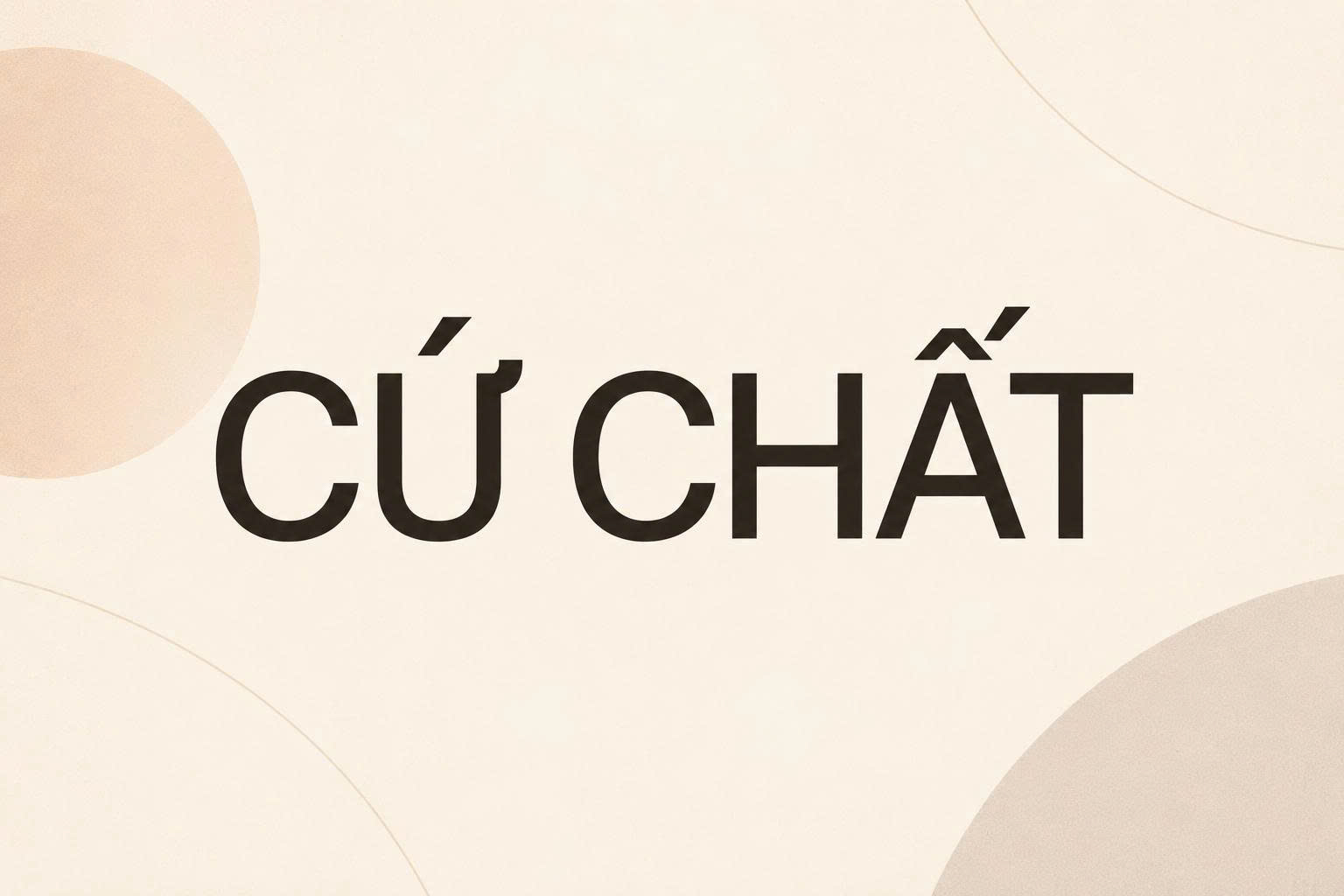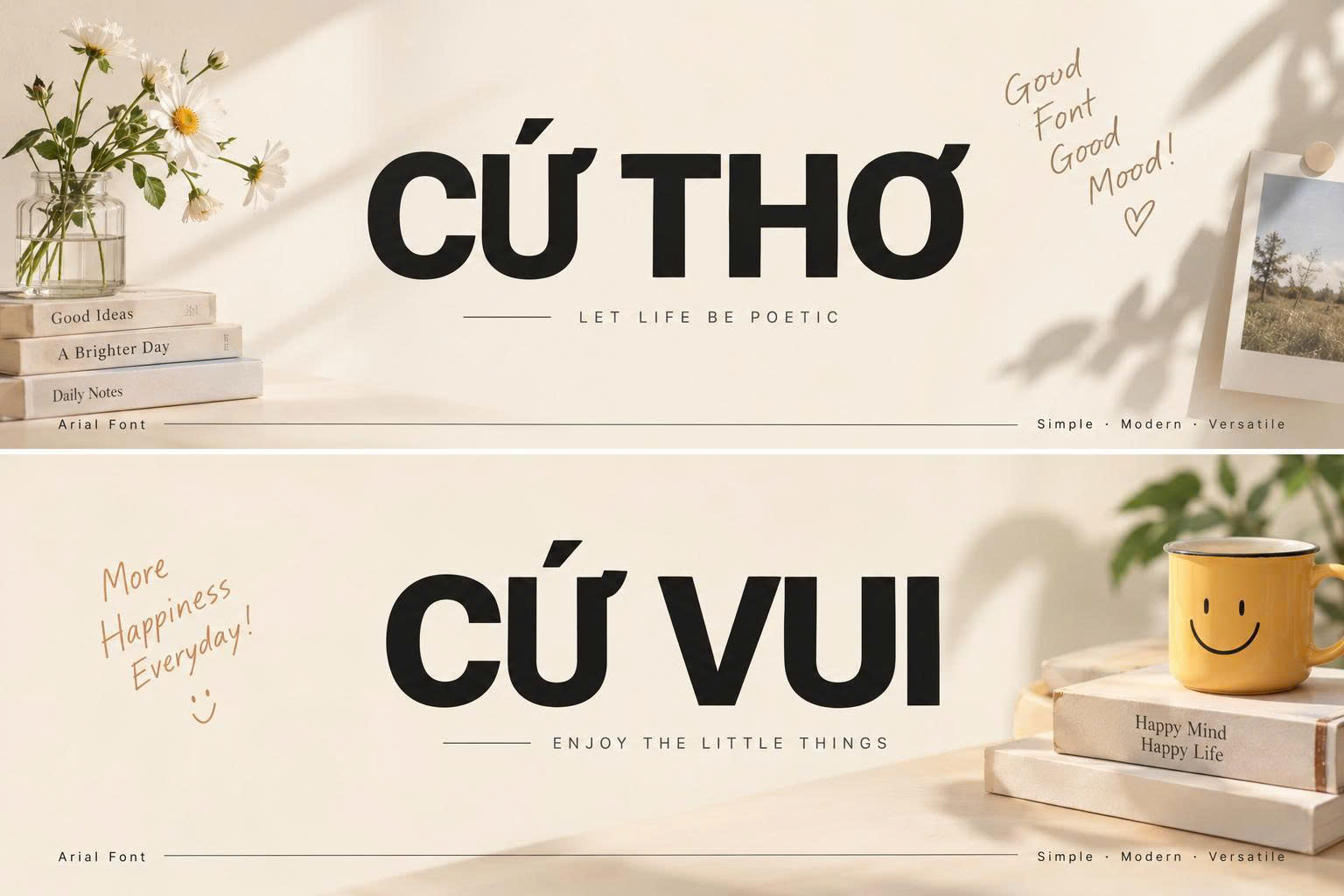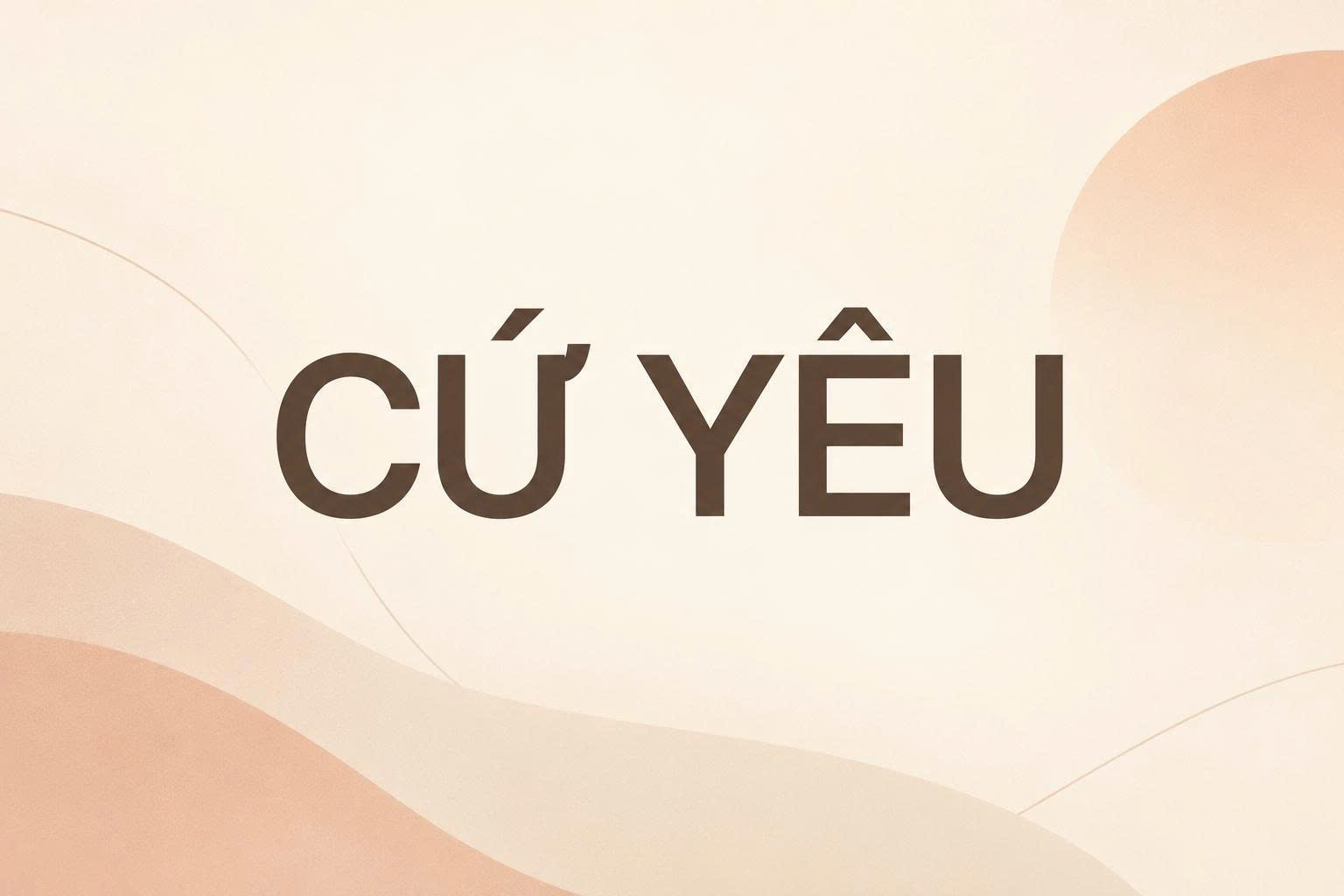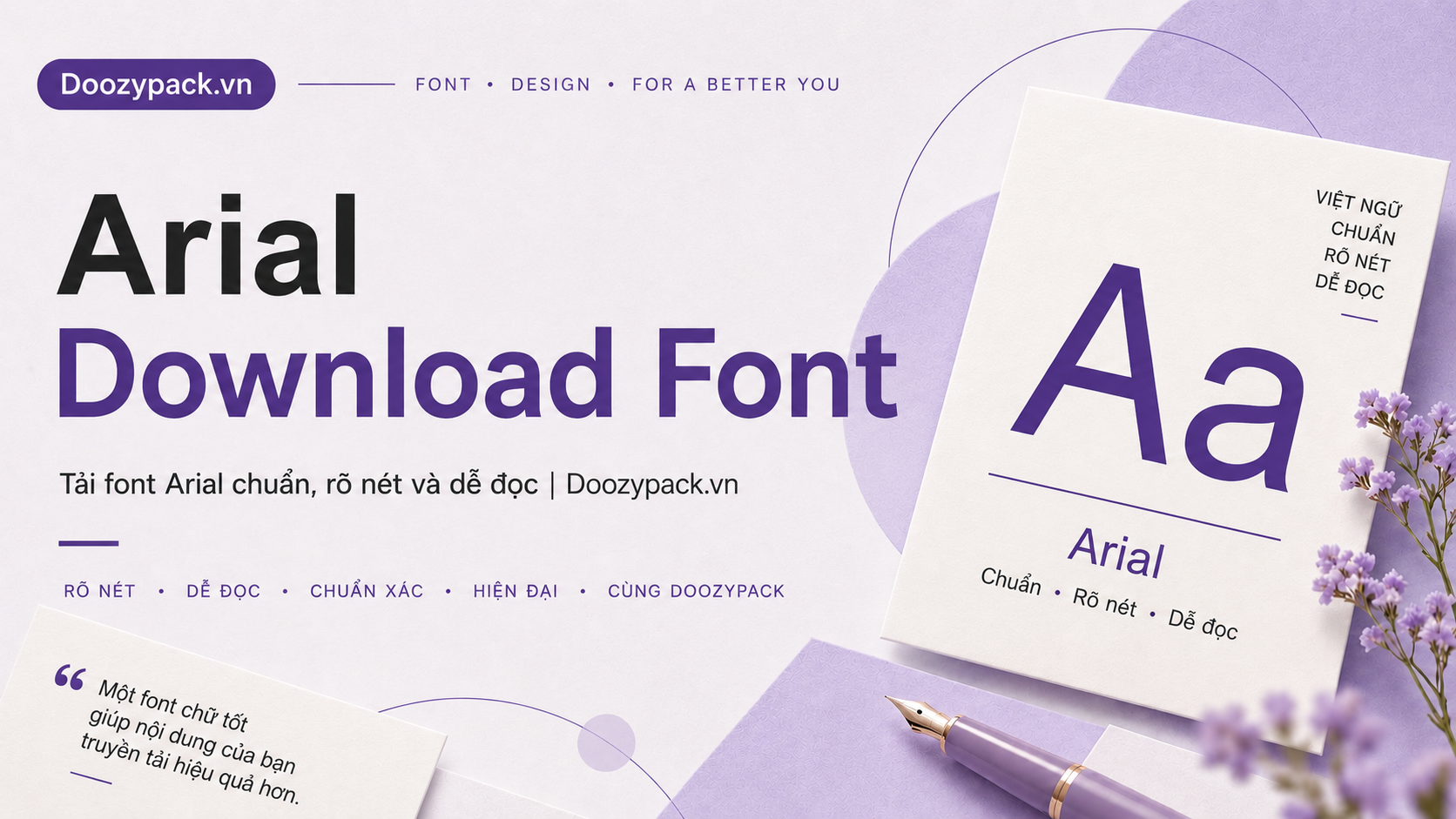
Arial download font là từ khóa được tìm kiếm nhiều nhất khi designer và nhân viên văn phòng cần một bộ phông chữ không chân (Sans-serif) tiêu chuẩn, hiện đại và có độ tương thích tuyệt đối. Được thiết kế bởi Monotype, Arial đã trở thành “phông chữ quốc dân” nhờ cấu trúc chữ minh bạch, rõ nét và cực kỳ dễ đọc trên mọi thiết bị. Doozypack.vn chia sẻ link download font Arial trọn bộ, bao gồm các biến thể quan trọng như Narrow, Bold và Unicode MS để bạn hoàn thiện các bản thiết kế bao bì và văn bản chuyên nghiệp nhất.
Đặc điểm thiết kế vượt trội của phông chữ Arial
Arial không chỉ là một phông chữ hệ thống đơn thuần; nó là kết quả của sự nghiên cứu về tỉ lệ hình học để mang lại trải nghiệm thị giác trung tính và chuyên nghiệp nhất.
Tính đa dụng và độ dễ đọc cực cao
Đặc trưng lớn nhất của Arial là các đường nét dứt khoát, độ dày nét đồng đều và không có các chi tiết rườm rà. Thiết kế này giúp mắt người nhận diện ký tự nhanh chóng, giảm thiểu tình trạng mỏi mắt khi đọc các khối văn bản dài. Tại Doozypack.vn, chúng tôi luôn khuyên khách hàng sử dụng Arial cho các phần nội dung quan trọng trên bao bì như hướng dẫn sử dụng, bảng thành phần dinh dưỡng hoặc địa chỉ sản xuất.
Sự tương thích tuyệt vời trên mọi hệ điều hành
Arial là phông chữ tiêu chuẩn trên cả Windows và macOS. Việc sử dụng Arial giúp bản thiết kế của bạn giữ nguyên định dạng khi chuyển đổi giữa các máy tính khác nhau. Điều này đặc biệt quan trọng trong quy trình in ấn tại xưởng, giúp hạn chế tối đa rủi ro lỗi nhảy chữ hoặc lỗi font khi mở file sản xuất.
Tổng hợp các biến thể Arial phổ biến nhất hiện nay
Hệ gia đình font Arial cung cấp nhiều biến thể đặc thù để giải quyết từng bài toán không gian khác nhau trong thiết kế:
- Arial Unicode MS: Đây là bản “full” nhất hỗ trợ hàng chục nghìn ký tự của nhiều ngôn ngữ khác nhau. Việc download font arial unicode ms là giải pháp hoàn hảo cho các dự án tem nhãn hàng xuất khẩu hoặc bao bì đa ngôn ngữ.
- Arial Narrow: Tải font arial narrow giúp bạn tiết kiệm diện tích tối đa. Với cấu trúc chữ hẹp, biến thể này cho phép trình bày nhiều thông tin hơn trên các mặt bên của hộp giấy nhỏ mà vẫn đảm bảo tính thẩm mỹ.
- Arial Bold: Arial bold download font là lựa chọn số một để làm tiêu đề phụ, tên sản phẩm hoặc các lưu ý quan trọng cần thu hút thị giác mạnh.
| Biến thể Font | Đặc điểm thị giác | Mục đích sử dụng đề xuất tại Doozypack.vn |
| Arial Regular | Cân đối, dễ đọc | Dùng cho nội dung mô tả, bảng thành phần (Body text). |
| Arial Bold | Vững chãi, nổi bật | Dùng làm tiêu đề, tên sản phẩm hoặc thông số kỹ thuật chính. |
| Arial Narrow | Hẹp, tiết kiệm diện tích | Dùng cho nhãn dán chai lọ nhỏ hoặc các mặt phụ của vỏ hộp. |
| Arial Unicode MS | Hỗ trợ đa ngôn ngữ | Thiết kế bao bì xuất khẩu sang các thị trường quốc tế. |
Gợi ý lựa chọn: Nếu bạn cần trình bày nhiều thông tin kỹ thuật trên một mặt tem nhãn hẹp, hãy ưu tiên download font arial narrow. Biến thể này giúp bạn hiển thị nhiều nội dung hơn mà không cần giảm kích thước chữ xuống quá nhỏ gây khó đọc cho người dùng.
Tại sao designer nên dùng Arial cho thiết kế bao bì tại Doozypack.vn?
Trong ngành thiết kế và sản xuất bao bì, Arial luôn là lựa chọn “an toàn” và hiệu quả nhất nhờ tính ứng dụng thực tế cao:
- Hiển thị sắc nét ở kích thước nhỏ: Ngay cả khi in ở size chữ 5pt – 6pt trên tem nhãn dán sản phẩm, Arial vẫn duy trì được hình khối rõ ràng, không bị bết mực.
- Dễ dàng phối hợp: Nhờ tính trung tính, bạn có thể dễ dàng kết hợp Arial với một font viết tay (Script) nghệ thuật hoặc font có chân (Serif) sang trọng để tạo sự tương phản.
- Tính chuyên nghiệp: Arial mang lại diện mạo chỉn chu, hiện đại, rất phù hợp cho các dòng bao bì dược phẩm, thực phẩm chức năng và linh kiện điện tử.
03 Lưu ý kỹ thuật khi in ấn với font Arial
Sản xuất bao bì sử dụng phông chữ như Arial đòi hỏi designer cần lưu ý một số vấn đề kỹ thuật tại xưởng in chuyên nghiệp:
- Kiểm soát độ tràn mực (Dot Gain): Do các khe hở trong chữ của Arial khá thoáng nên rất an toàn khi in Offset. Tuy nhiên, trên giấy Kraft thô nhám, bạn nên để size chữ tối thiểu từ 6pt trở lên.